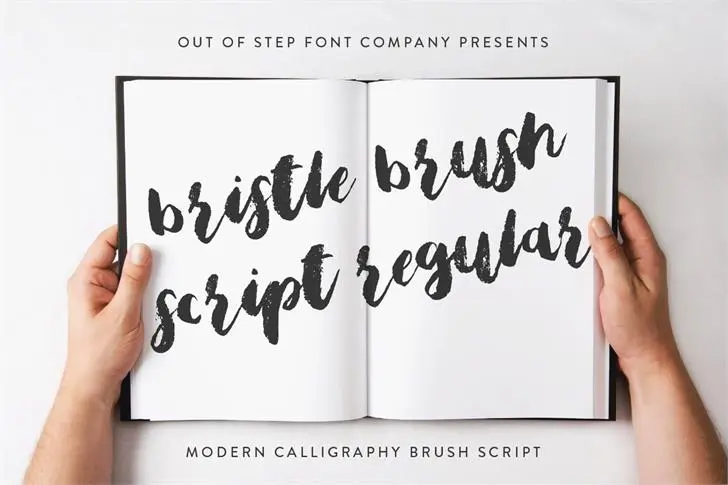
Bristle Brush Script Font – Download Grátis
A Bristle Brush Script Regular é uma tipografia feita sob medida para projetos modernos de escrituração chinesa ou calligrafia ocidental. Com seus traços grossos e espirais finas, esta fonte evoca a sensação do escrever com um grande pincel de lã quase acabado. Seus traços largos nas baixas são perfeitamente contrastados por os pontinhos finos na extremidade, criando um equilíbrio arquitetônico e único. Perfeito para criar design gráfico moderno, arte digital ou qualquer projeto que busque uma sensação de expressão artesanal em seus trabalhos. Não perca a oportunidade de adicionar um toque exclusivo à sua arte com esta fonte elegante.
Designer: Out Of Step Font Company